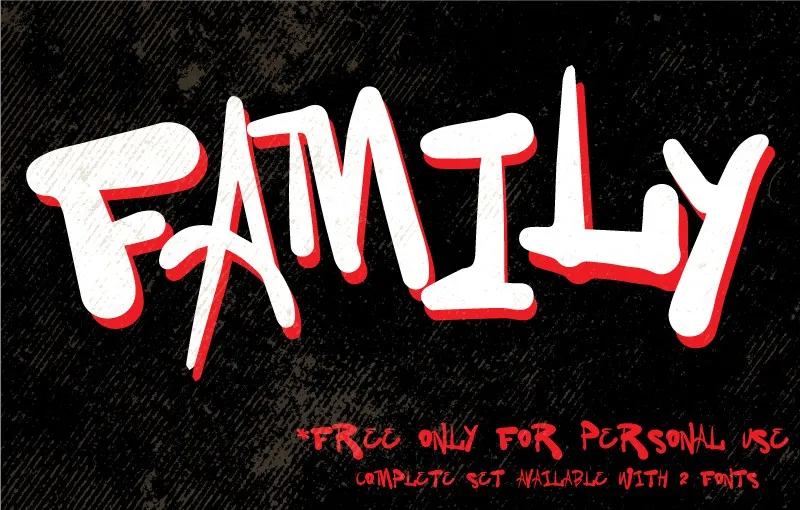
Vtks Family Font – Download Grátis
A Vtks Family Font é uma família completa de fontes com traços livres desenvolvida por Hamilton. Ela é perfeita para designers que buscam uma combinação única e moderna de linhas elegantes e detalhes cuidadosamente construídos. Ideal tanto para projetos comerciais quanto para aplicação em sites, materiais impressos ou design gráfico em geral. Composta por uma grande variedade de caracteres, a Vtks Family Font oferece um toque diferenciado que se adapta perfeitamente aos seus esforços criativos. Suas linhas leves e definidas combinam com elementos detalhadamente personalizados para criar resultados incríveis em qualquer aplicação. Ideal tanto para designers de interface do usuário quanto para aqueles que trabalham com design editorial, a Vtks Family Font oferece uma excelente opção para quem busca uma fonte moderna e criativa que se destaca entre as demais. Seja você um ator no mercado ou apenas iniciando, a Vtks Family Font tem o poder de transformar seus projetos em algo único e memorável. Aproveite sua compra da licença e descubra por si mesmo todas as possibilidades desta família fantástica de fontes.